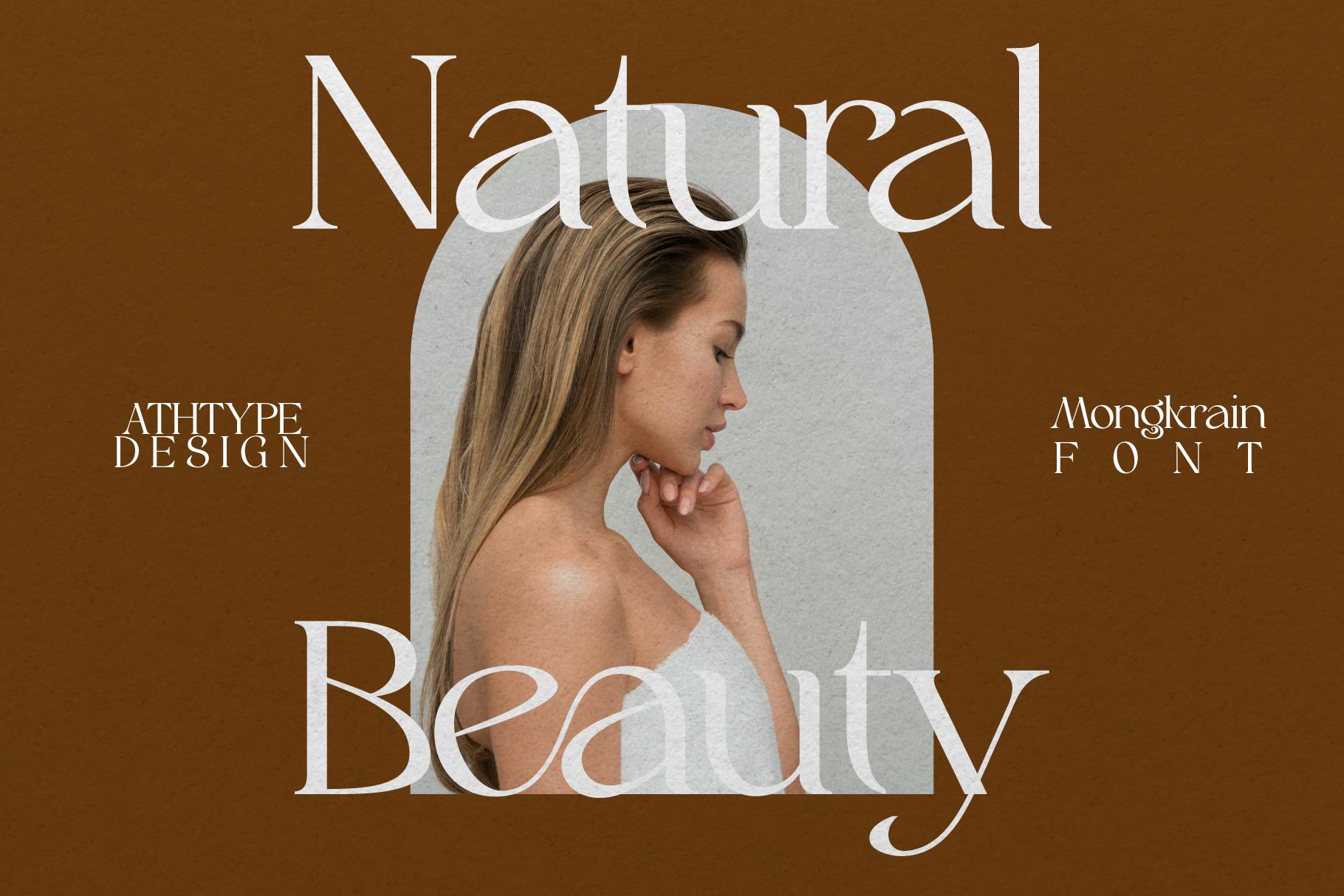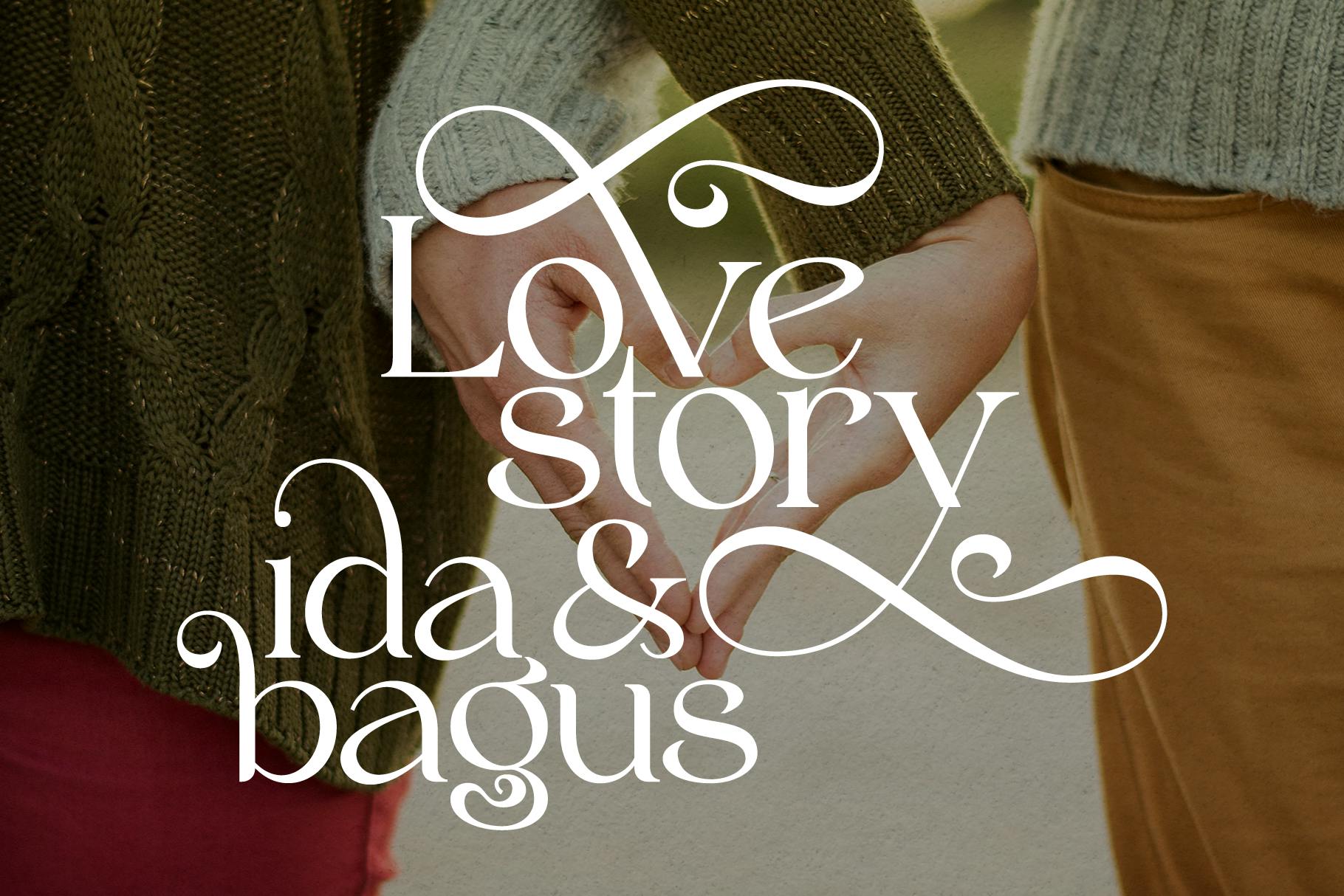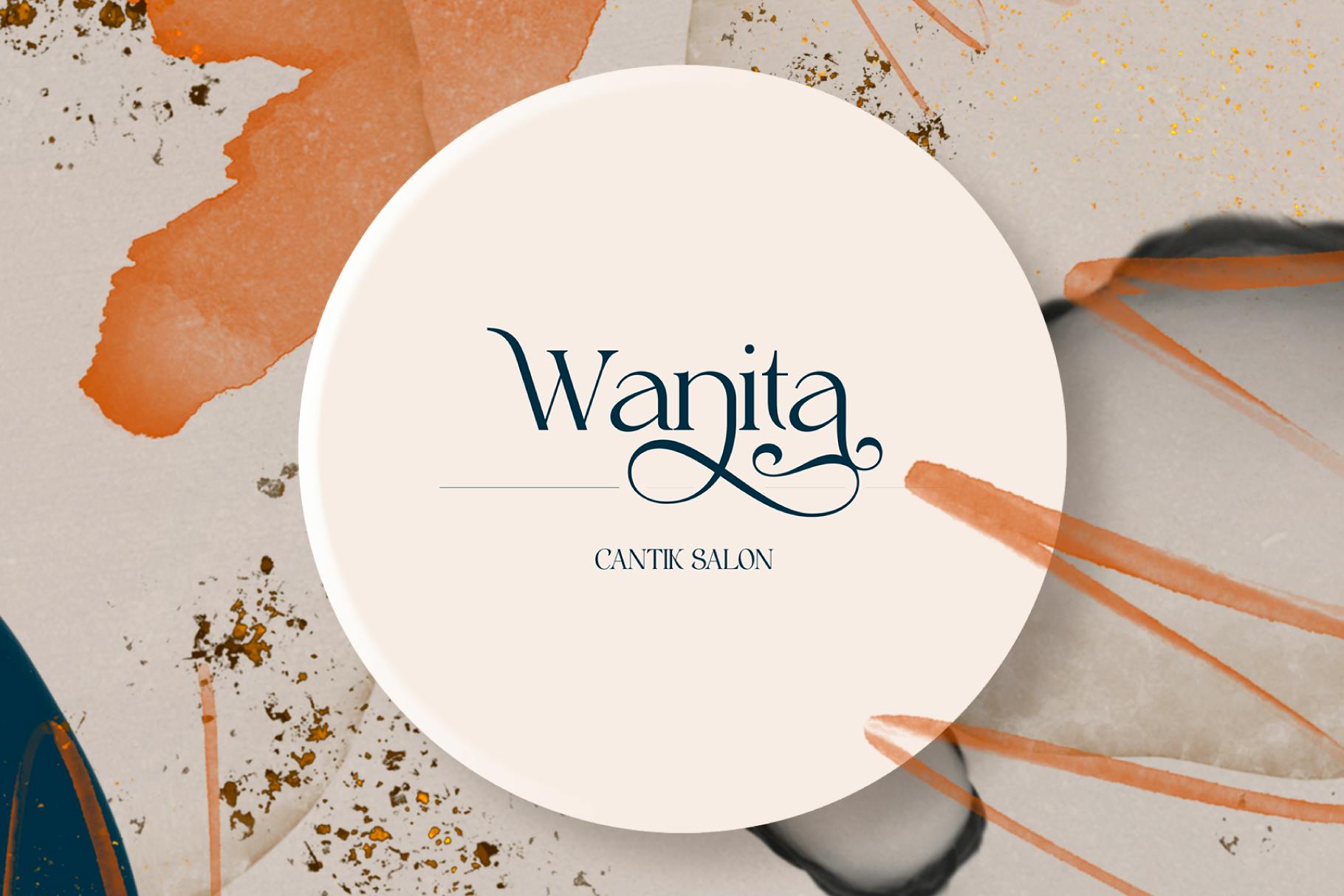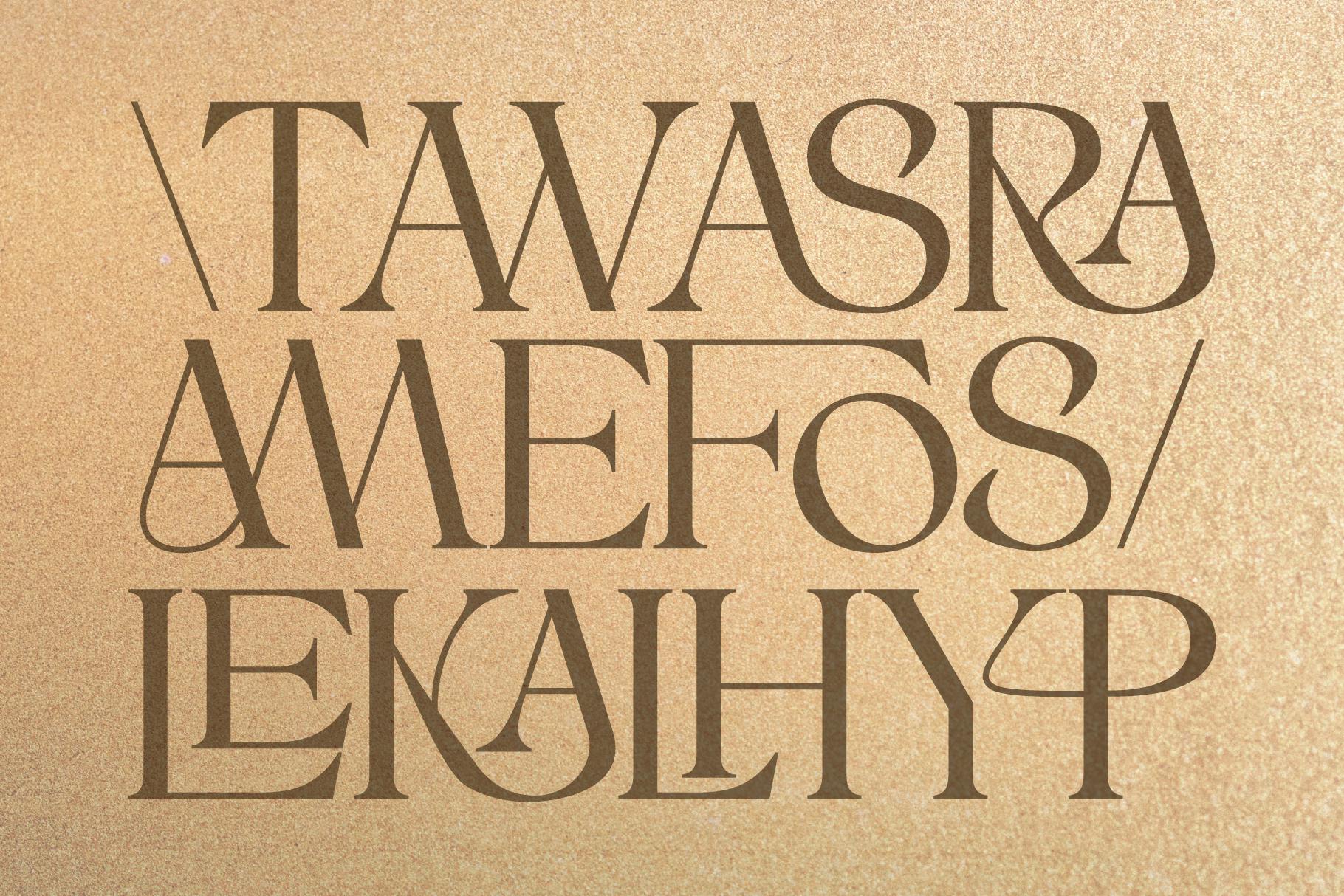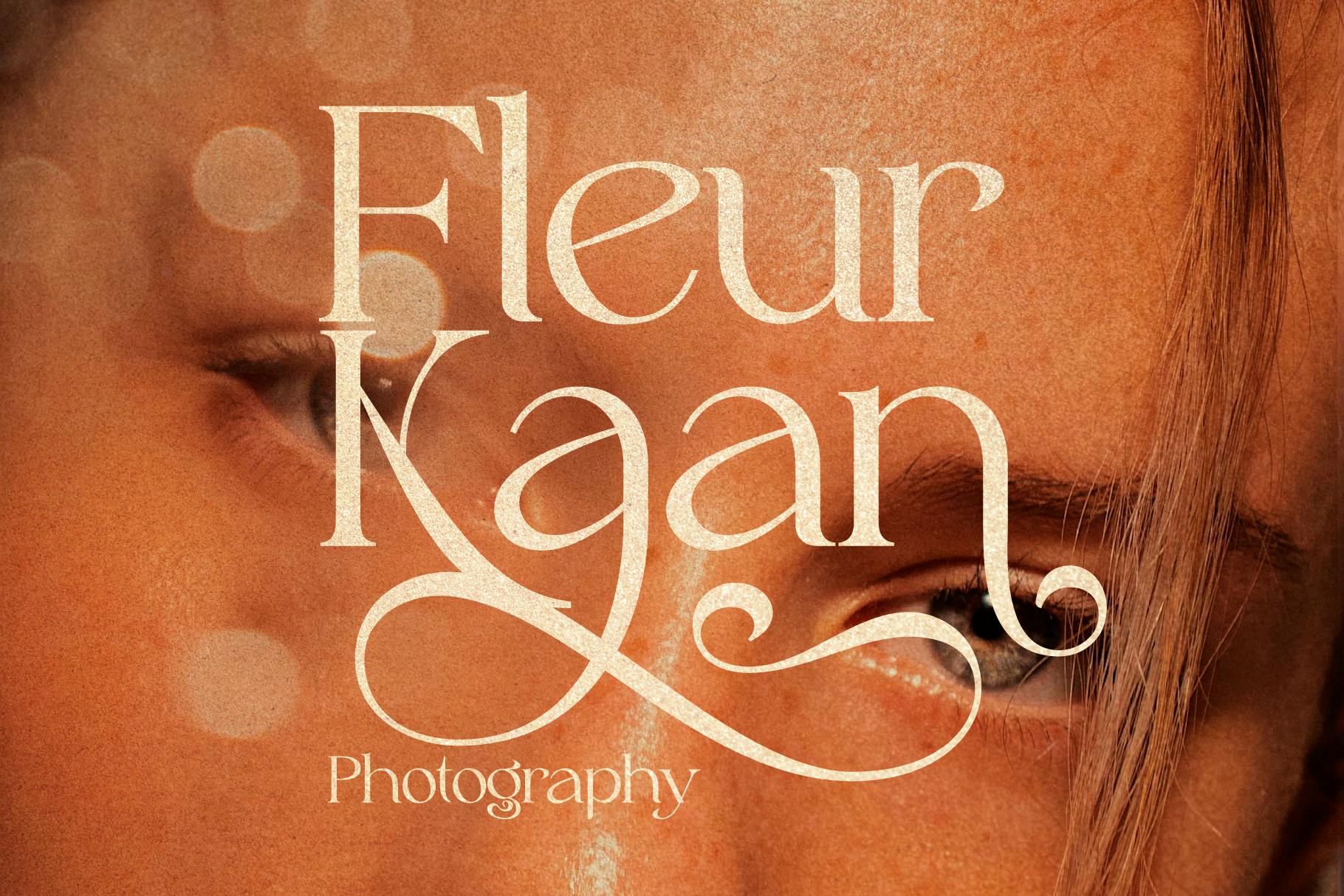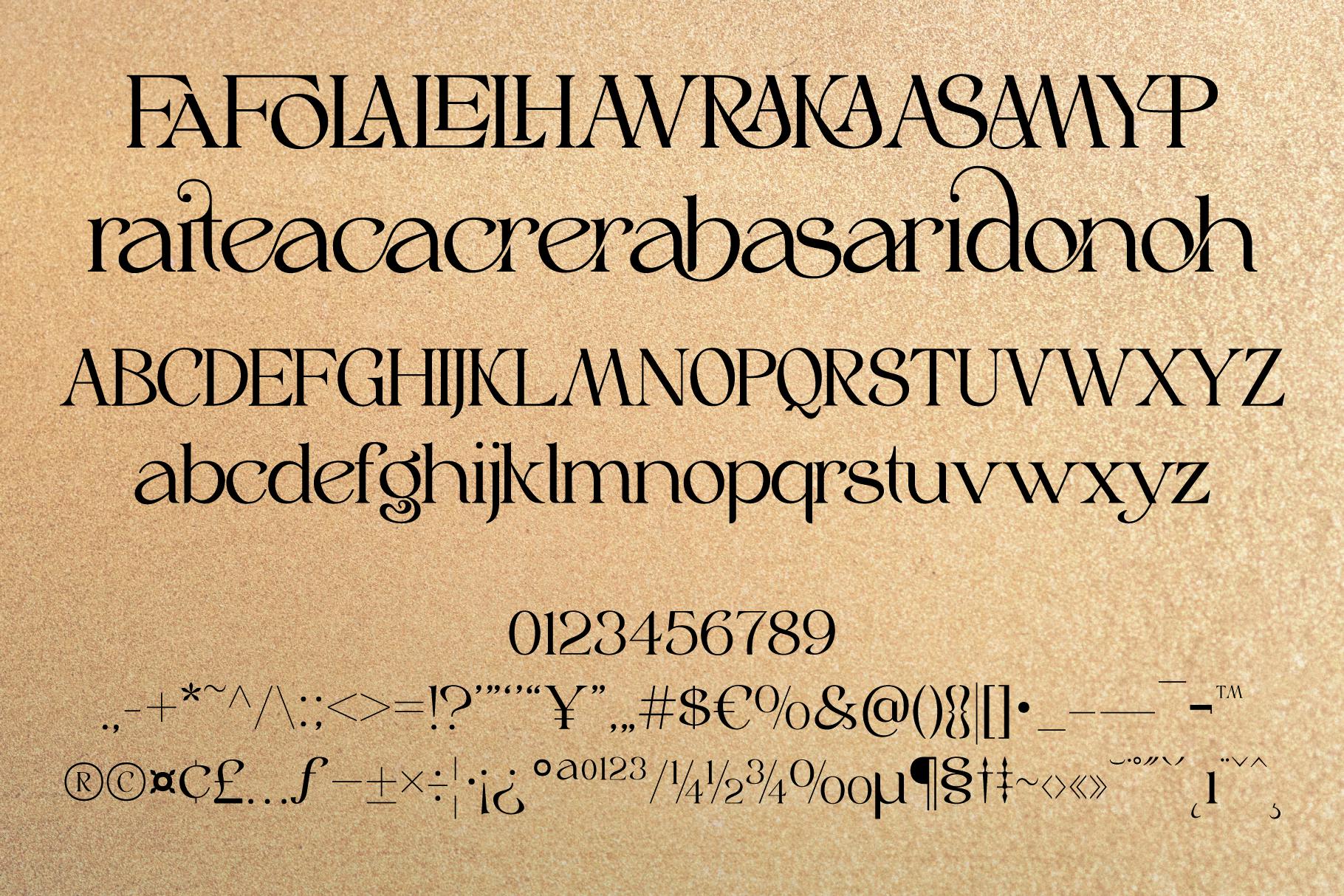
فونت Mongkrain - یک فونت لوکس و شیک از Authen Type است. طراحیهای کلاسیک و زیبا این فونت را برای طراحیهای برندینگ محصولات زیبایی و زنانه بسیار مناسب میسازد.
فونت Mongkrain همچنین برای طرحبندیها، بروشورها، لوگوها و دعوتنامهها با مفاهیم مختلف فونت جالب توجه خواهد بود.